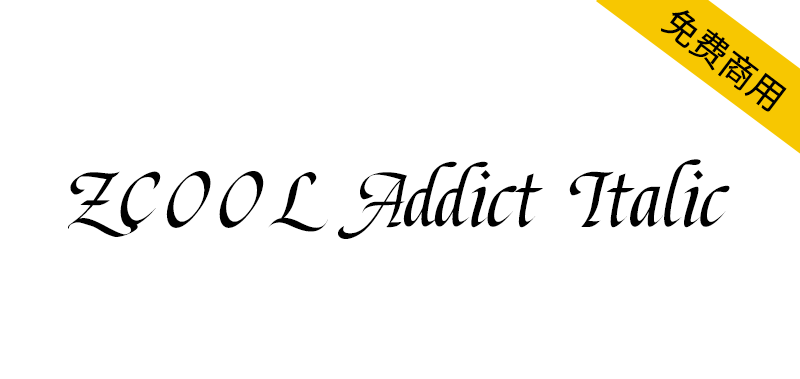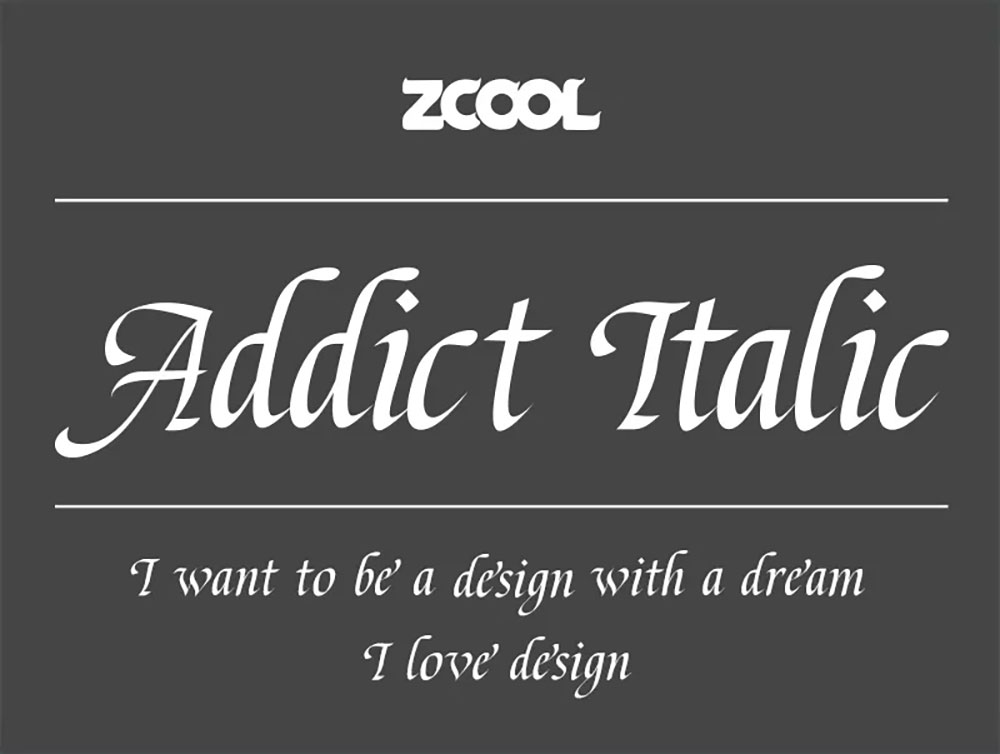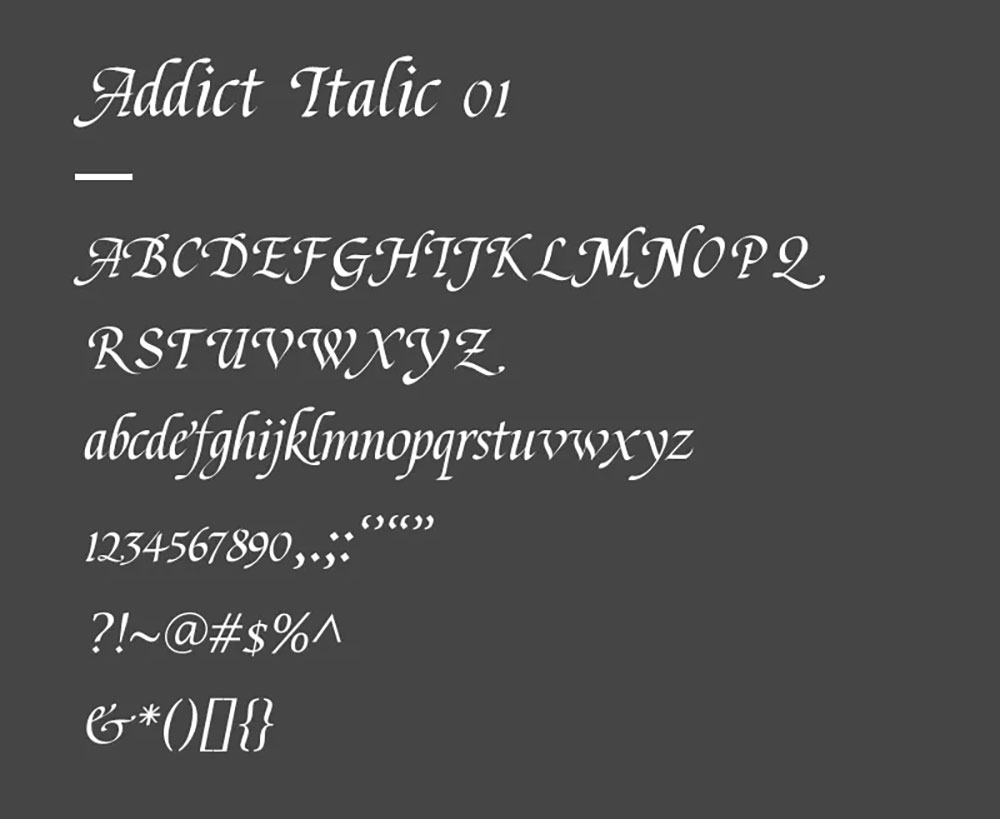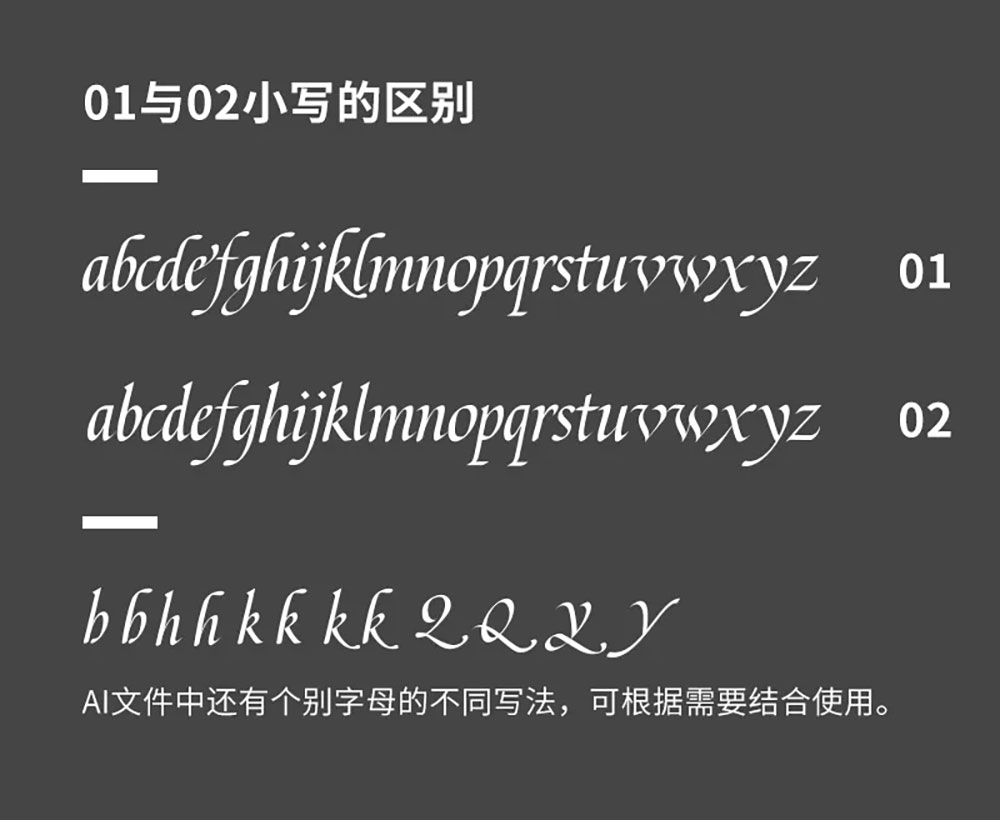
站酷意大利体(ZCOOL Addict Italic)是由站酷作者大猫Addict设计,站酷冠名的首款公益西文字库, 52个字母,10个数字,24个符号。是可免费商用的西文字,2016年5月发布第一版。
站酷意大利体是手写的意大利体风格,通过平行笔手写大量字母,挑选写的还不错的进行扫描,最后矢量处理成英文字库,并生成了TTF字体文件,下载的压缩文件中有三个文件,ZCOOL Addict Italic 01、ZCOOL Addict Italic 02两个字体安装文件和一个包含字母和标点的AI文件。01与02的区别主要是小写字母的写法有所不同,实际使用中两者可结合使用。